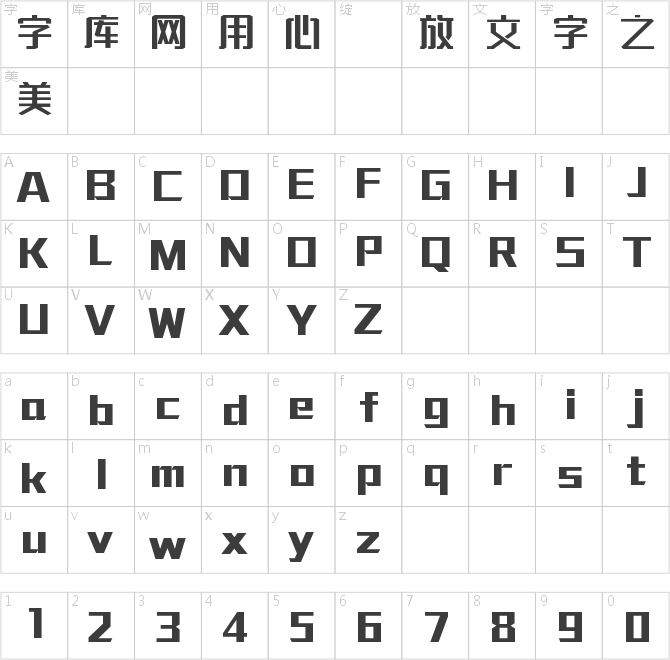
2020年4月初,素材集市招募十二名各行業(yè)現(xiàn)役設計師,組建了字集團隊,“素材集市酷方體”是字集團隊的首款原創(chuàng)字庫。經(jīng)過幾個月的艱苦奮戰(zhàn),“素材集市酷方體”已完成了漢字+字符2628個,能基本滿足一般的設計需求。素材集市酷方體于2020年8月10日(星期一)正式發(fā)布!并且是免費商用!免費商用!免費商用!
素材集市酷方體字體字庫是一款讓人賞心悅目、百看不厭的中文字體,適合各類廣告和產(chǎn)品包裝設計應用,字體大小0.45MB,格式為ttf字體,上傳用戶是迷路的豬,作者/版權方為素材集市